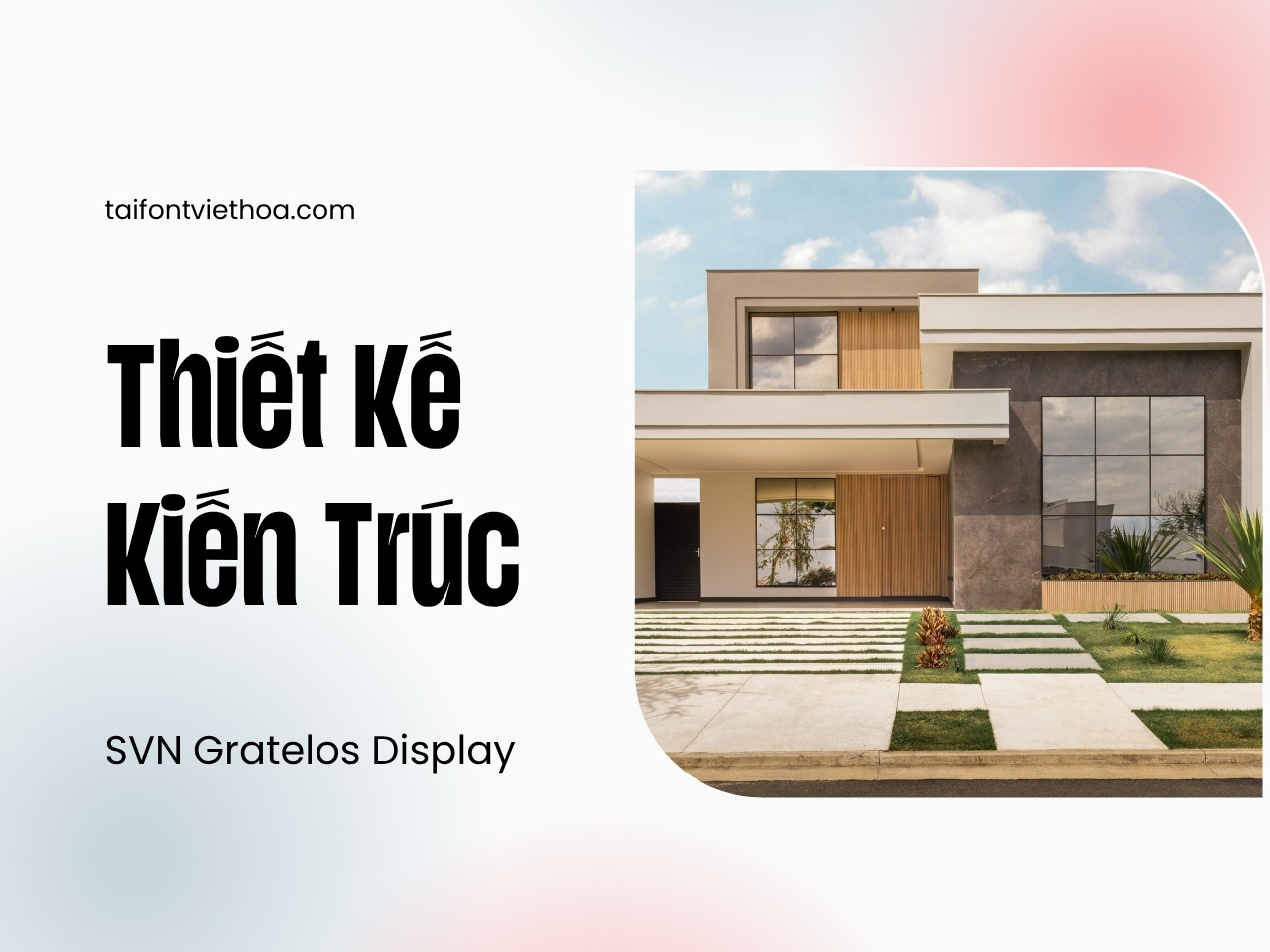
Giới thiệu về font SVN Gratelos Display – Kiểu chữ display hiện đại, nổi bật và ấn tượng
SVN Gratelos Display là phiên bản Việt hóa của font Gratelos Display – một kiểu chữ display mang phong cách hiện đại, nổi bật và thu hút. Font được thiết kế với các nét chữ đậm, sắc nét và có kiểu dáng độc đáo, rất phù hợp cho các dự án thiết kế tiêu đề, poster, quảng cáo và nhận diện thương hiệu.
Phiên bản Việt hóa của SVN Gratelos Display đã được Taifontviethoa.comhoàn thiện kỹ lưỡng, hỗ trợ đầy đủ dấu tiếng Việt cùng hơn 60 ngôn ngữ khác. Font giúp các nhà thiết kế dễ dàng áp dụng trong các sản phẩm sáng tạo đa dạng, giữ được phong cách nổi bật và cá tính.
Thiết kế display ấn tượng – Ứng dụng linh hoạt trong quảng cáo và thương hiệu
SVN Gratelos Display sở hữu các nét chữ dày, rõ ràng và cá tính với thiết kế độc đáo, tạo cảm giác mạnh mẽ và thu hút. Font rất phù hợp cho tiêu đề, banner, poster hoặc logo cần sự nổi bật và ấn tượng cao. Phong cách thiết kế của Gratelos Display đặc biệt thích hợp với các dự án quảng cáo, sự kiện và nhận diện thương hiệu sáng tạo.
Ứng dụng lý tưởng: thiết kế poster quảng cáo, banner sự kiện, logo thương hiệu, bao bì sản phẩm và các dự án marketing sáng tạo. Ngành nghề phù hợp: quảng cáo, sự kiện, giải trí, thời trang và các thương hiệu định vị theo phong cách hiện đại, nổi bật.